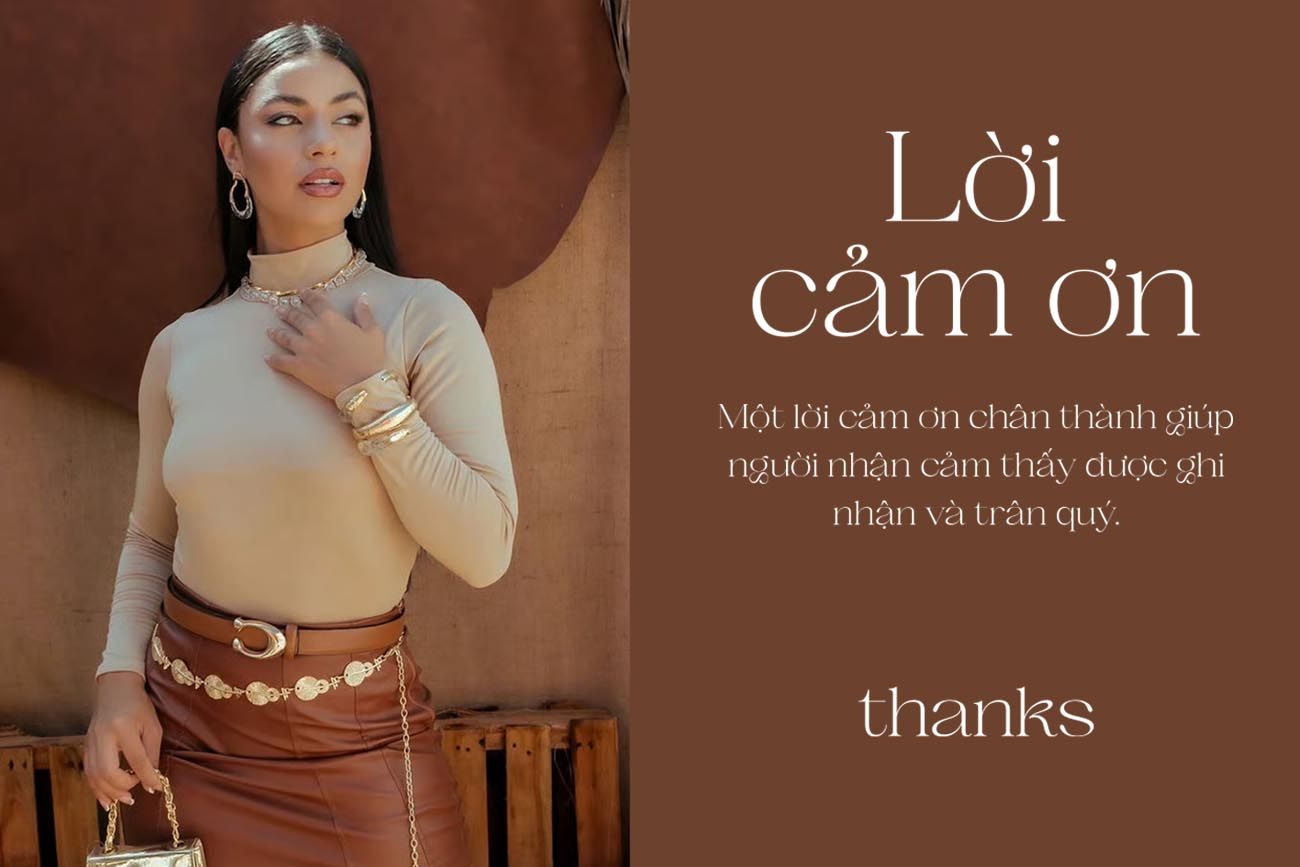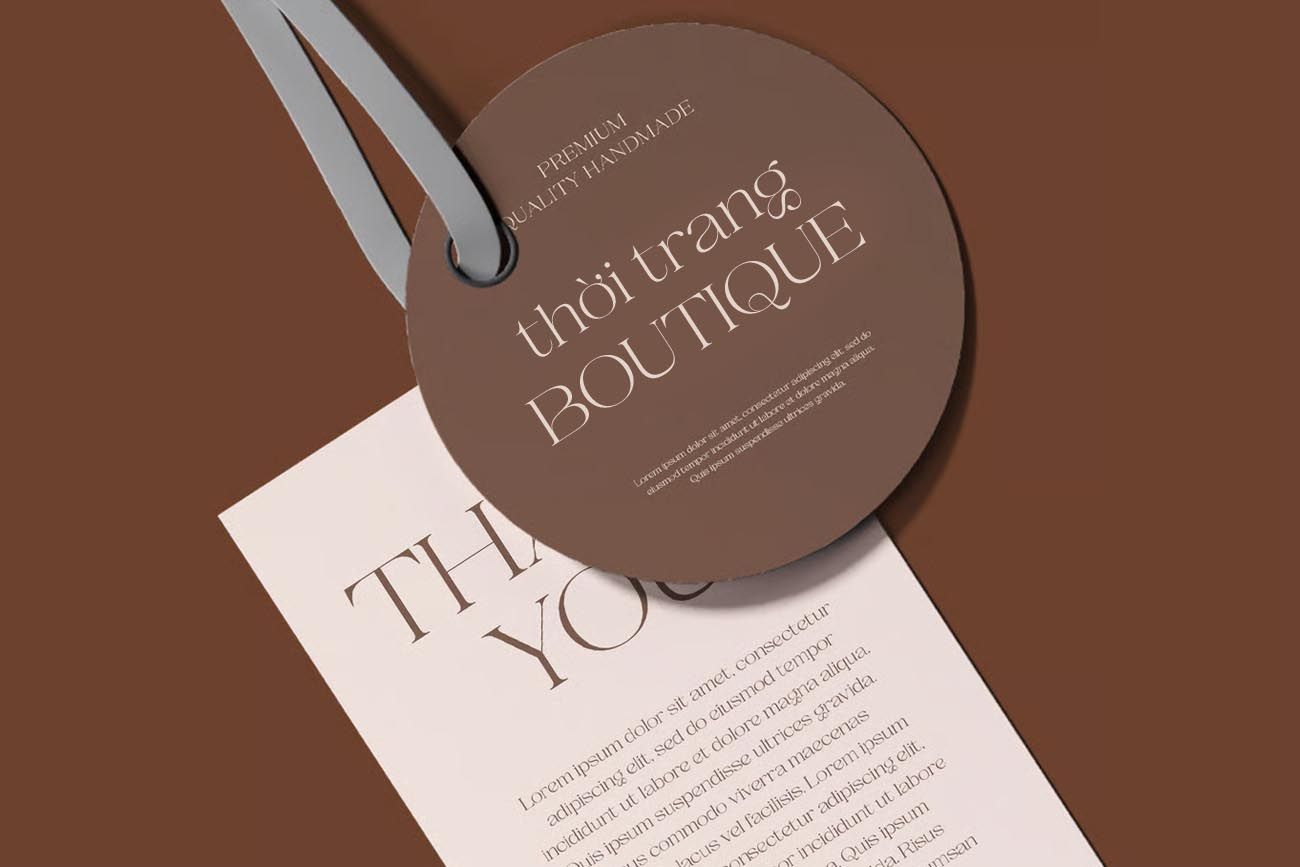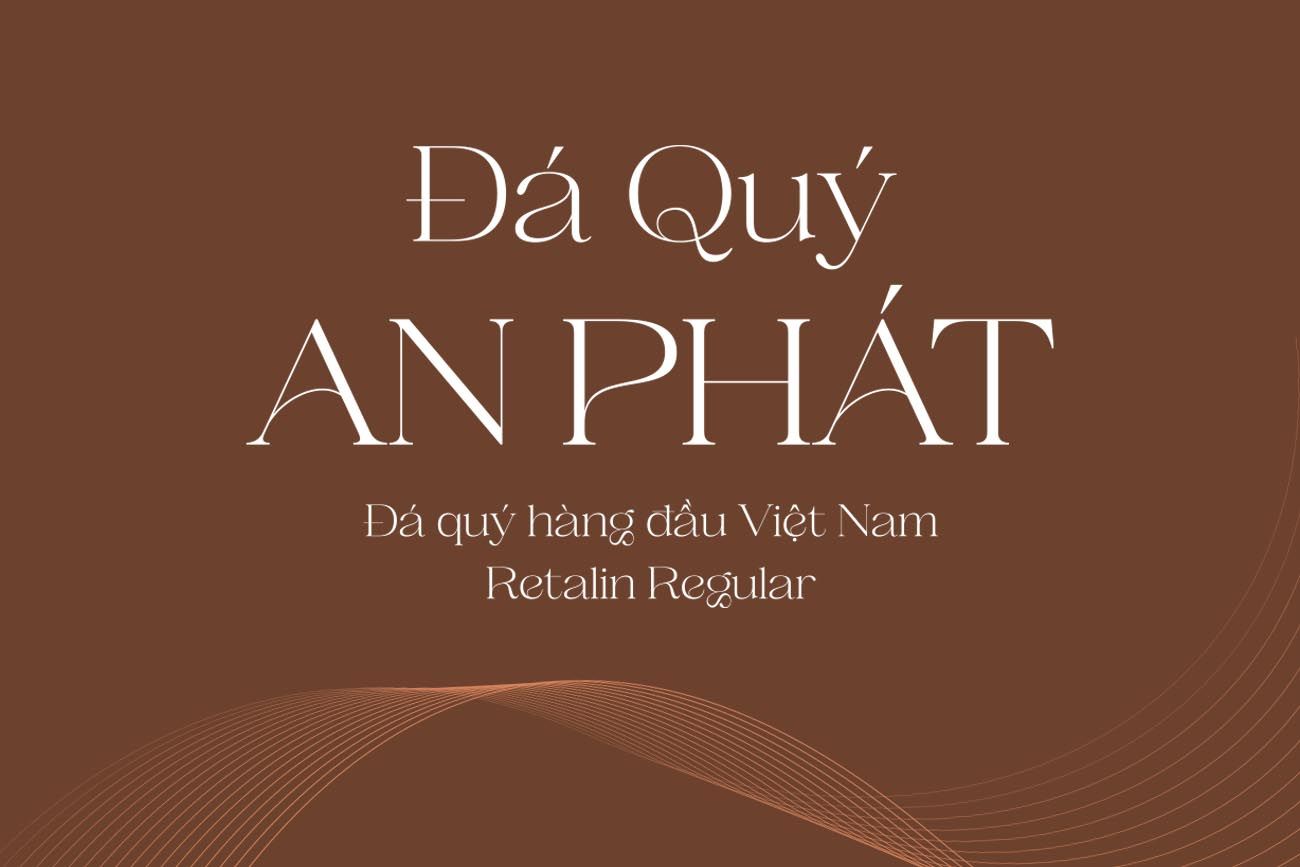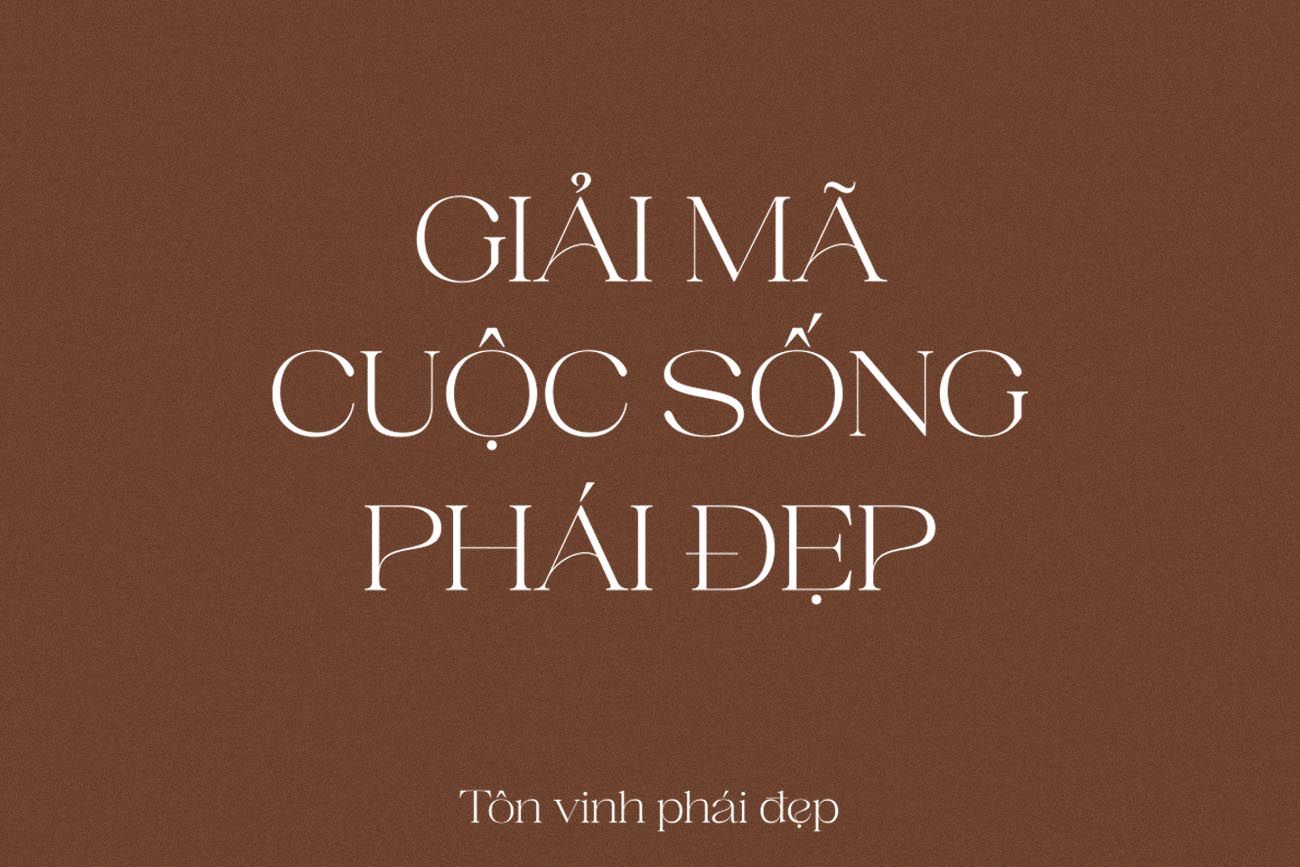
TH Retalin Regular là một kiểu font serif mang phong cách hiện đại, quý phái và tinh tế. Với những đường nét thanh mảnh, chân chữ sắc sảo và sự tương phản tinh tế giữa các nét dày – mảnh, Retalin nhanh chóng trở thành lựa chọn yêu thích của các nhà thiết kế trong lĩnh vực mỹ phẩm, thời trang cao cấp, logo spa và ấn phẩm tạp chí.
Font Retalin sở hữu cấu trúc có chân (serif) nhưng được thiết kế với tỷ lệ thanh thoát, đem lại cảm giác vừa cổ điển vừa hiện đại. Nét chữ mảnh mai, gọn gàng nhưng không hề yếu đuối – ngược lại, nó thể hiện sự tự tin và nét thanh lịch đặc trưng của các thương hiệu cao cấp.
Một vài đặc trưng dễ nhận biết của Retalin Regular:
Chữ hoa cao, có độ thanh thoát mạnh, tạo nên ấn tượng nổi bật ở tiêu đề, logo hay tên thương hiệu.
Nét móc uốn cong mềm mại nhưng dứt khoát, đem lại cảm giác quyến rũ mà không màu mè.
Hỗ trợ đầy đủ tiếng Việt, bao gồm các dấu, chữ đặc biệt như “Ă”, “Ê”, “Đ”, giúp bạn dễ dàng sử dụng trong thiết kế nội địa mà không cần chỉnh sửa thêm.
Retalin Regular phù hợp với nhiều loại dự án cần yếu tố sang trọng, thanh lịch và tinh tế, đặc biệt là:
Font chữ cho thiết kế mỹ phẩm: Retalin giúp bao bì trở nên cao cấp, gợi cảm giác tin tưởng và nữ tính.
Font chữ cho thương hiệu thời trang: Gợi nhớ đến các thương hiệu châu Âu thanh lịch, tạo phong thái chuyên nghiệp.
Font chữ làm logo spa: Đầy cảm xúc, mềm mại và duyên dáng – cực kỳ hợp với spa, wellness hoặc dịch vụ làm đẹp.
Font chữ cho tạp chí thời trang: Retalin tạo điểm nhấn ấn tượng cho tiêu đề, đặc biệt trên các bìa ấn phẩm cao cấp.
Font chữ cho thiết kế bao bì sản phẩm: Dễ đọc, nổi bật, nhưng vẫn giữ được sự trang nhã và hài hòa.
Nếu bạn đang tìm một font chữ sang trọng, thanh lịch và phù hợp với các thiết kế dành cho phái đẹp, Retalin Regular là lựa chọn không thể bỏ qua. Với khả năng hỗ trợ tiếng Việt, kiểu dáng thời thượng và ứng dụng linh hoạt, Retalin sẽ giúp bạn tạo nên những thiết kế đầy cảm xúc và chuyên nghiệp.